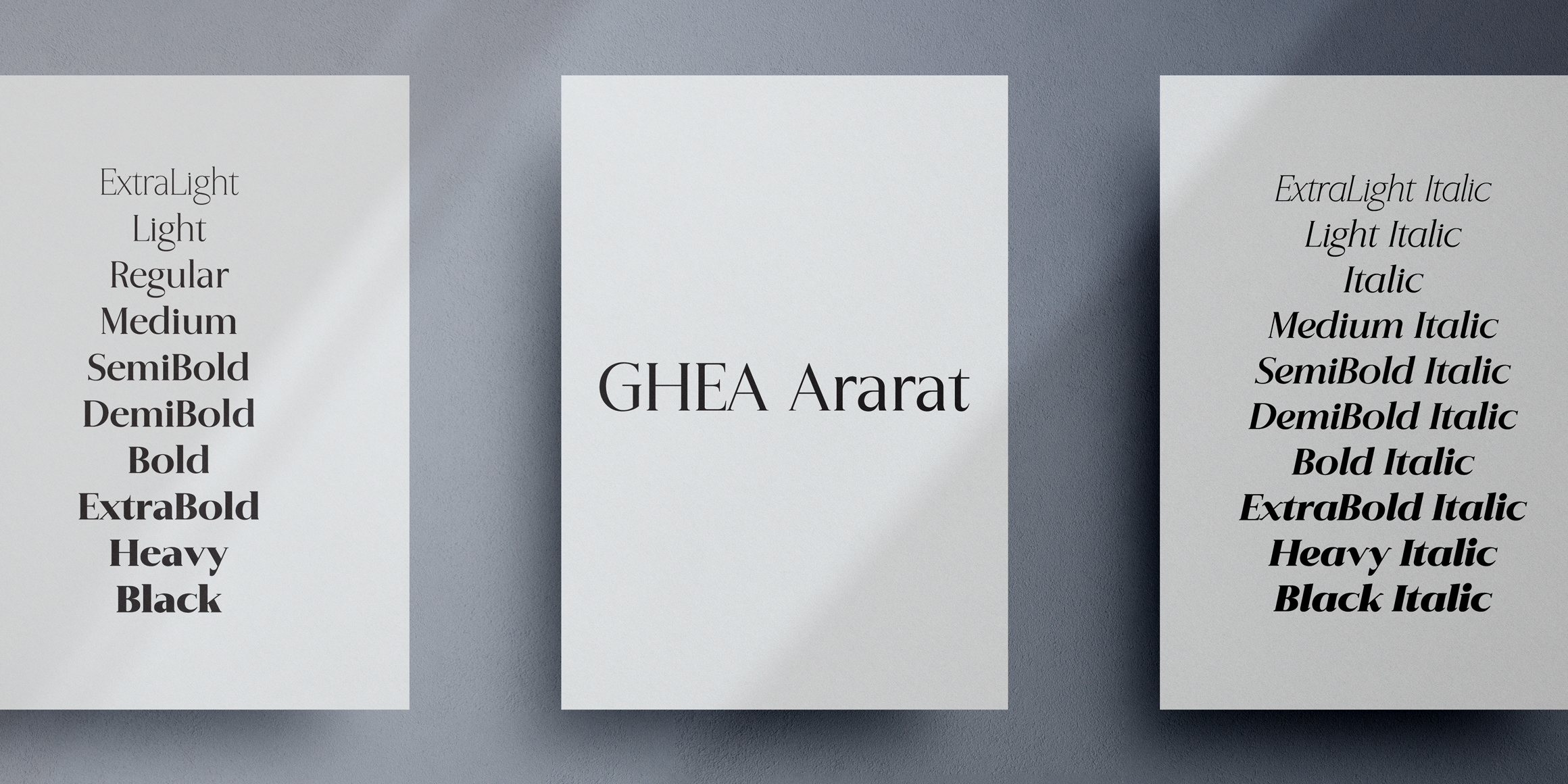
이번 강연에는 산돌의 오랜 파트너이자, 산돌구름에서 많은 사랑을 받고 있는 다국어 폰트 브랜드
게아폰트(GHEA Fonts)’의 창립자 에딕 가부지얀(Edik Ghabuzyan) 님이 연사로 참여합니다.
게아폰트(GHEAfonts)란?
에딕 가부지얀 님이 설립하신 게아폰트(GHEA Fonts)
산돌구름에 가장 오래전부터 입점해 꾸준히 사랑받아온 파운드리 중 하나입니다.
클래식하면서도 독특한 조형미로 마니아층을 형성해 온 게아폰트는
모든 폰트가 라틴뿐만 아니라 아르메니아 문자도 지원된다는 점, 알고 계셨나요?
그럼 이제부터 산돌구름에서 만나볼 수 있는 게아폰트의 추천 폰트들을 소개해 드릴게요.
1. GHEA Ararat
GHEA Ararat font in use
「GHEA Ararat」은 게아폰트를 대표하는 획 대비가 높고 우아한 디스플레이 세리프입니다.
부드러운 곡선과 고전적인 느낌이 인상적인 이 폰트는 무려 10종의 굵기를 지원해, 다양한 무드와 톤에 맞춰 연출이 가능합니다.
2. GHEA Hayk Title
GHEA Hayk Title font in use
「GHEA Hayk Title」은 높은 획 대비와 ball terminal 이라고 하는 획 끝 동그란 포인트가 특징인 폰트입니다.
브랜딩이나 헤드라인 등 크게 주목받고 싶은 지면에 사용하기에 제격이죠.
3. GHEA Lilit
GHEA Lilit font in use
마지막으로 「GHEA Lilit」 은 Regular 웨이트로 쓸 경우 긴 글줄에도 깔끔한 가독성을 자랑하는 세리프 폰트입니다.
Heavy Italic 웨이트 같은 경우는 화려한 연말 패키징 등에 잘 어울릴 것 같지 않나요?